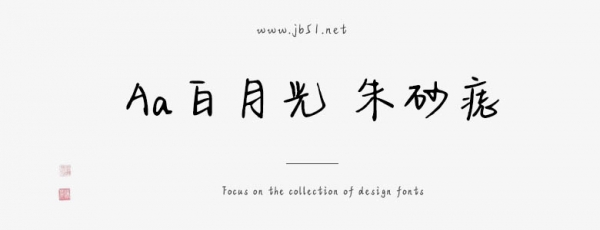
Aa白月光 朱砂痣是一款不錯(cuò)的藝術(shù)字體,由Aa字庫出品,字體筆觸略細(xì),書寫流暢,擁有字符數(shù)10329和字形數(shù)10297,具有很好的視覺感,適合應(yīng)用于藝術(shù)設(shè)計(jì)、平面宣傳設(shè)計(jì)、網(wǎng)頁設(shè)計(jì),書法字帖等領(lǐng)域,需要的朋友可以前來本站下載。